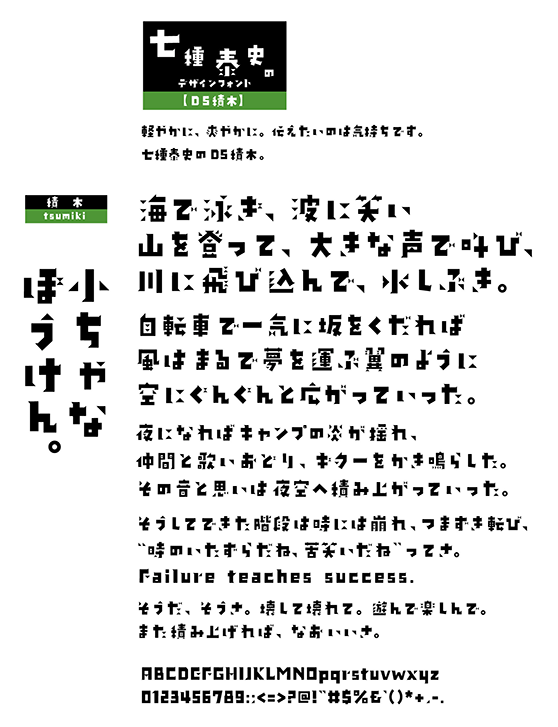
株式会社デザインシグナル
DS積木 (DS-tsumiki)
DS-tsumiki
遊んで楽しんで。冒険心のある書体です。
デザインシグナルセレクト版収録文字数 全3,809文字
【第一水準2965文字+第二水準444文字+仮名.約物.アルファベット400文字】
七種泰史/デザインシグナルの紹介
こころのこもった文字創りを目指す七種泰史氏のオリジナルブランド「デザインシグナル」。2008年夏からスタートし、年に2~3書体のペースで開発を進行中。多くのファンが新作を心待ちにする人気のブランド。